Nach dem Erfolg der ersten Ausgabe des TypoJournal (Fontblog berichtete) lag die Latte für Heft 2 hoch. Doch Herausgeber und Chefredakteur Ralf Herrmann überquert sie locker … mit der Ausgabe 2 seines typografischen Journals.
Der Umfang des Magazins hat sich nahezu verdoppelt. Die Liste der Autoren, die exklusiv Beiträge für das neue TypoJournal geschrieben haben, ist bemerkenswert: Erwin K. Bauer, Helmut Ness, Tim Ahrens und Dan Reynolds sind beispielsweise mit dabei.
Die zweite Ausgabe steht unter dem Motto »Wayfinding & Lesbarkeit«. Zunächst wird das Mysterium Lesbarkeit von Ralf Herrmann beleuchtet: »Das Zwiebelschichtenmodell der Lesbarkeit«. Wie lesen wir wirklich? Was hat es mit den so genannten Wortbildern auf sich? Sind Antiqua-Schriften wirklich besser lesbar als Groteskschriften? Warum werden Schriften für unterschiedliche Schriftgrößen geschaffen? Außerdem untersucht das Heft die Lesbarkeit von Leitsystemen im Spannungsfeld von Funktionalität und Ästhetik. Wie müssen Schriften für Beschilderungen gestaltet sein und wir können sich Besuchern in Messehallen oder ganzen Städte gut zurechtfinden?
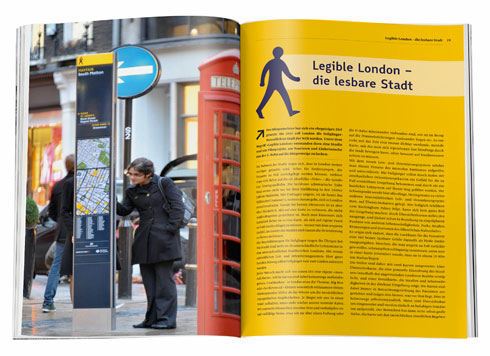
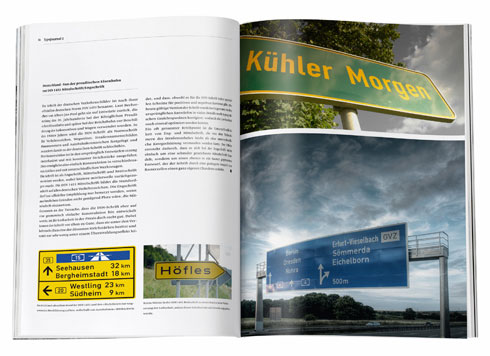
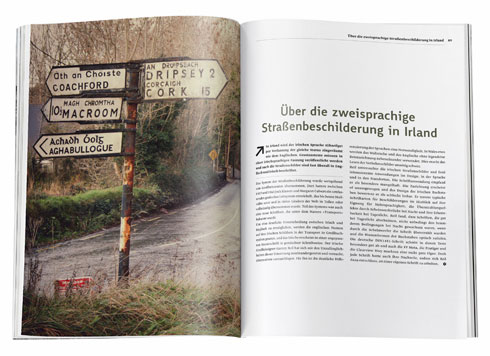
Einige der Themen im neuen TypoJournal:
- Lesen für Fortgeschrittene (Erwin K. Bauer)
- Legible London — die lesbare Stadt
- Guerilla-Dienst für die Verkehrssicherheit
- Ein typografischer Spaziergang durch Berlin (Helmut Ness)
- Optische Größen in der Schriftentwicklung (Tim Ahrens)
- Die Schriftarten auf europäischen Verkehrsschildern
- Die Entwicklung der Wayfinding Sans
- Lesbarkeit im Rollendruck: Die Zeitungsschrift Malabar (Dan Reynolds)
- Das Leit- und Orientierungssystem der Messe Stuttgart (büro uebele)
- Mythos Wortbilder – Wie lesen wir wirklich?
- Über die zweisprachige Straßenbeschilderung in Irland